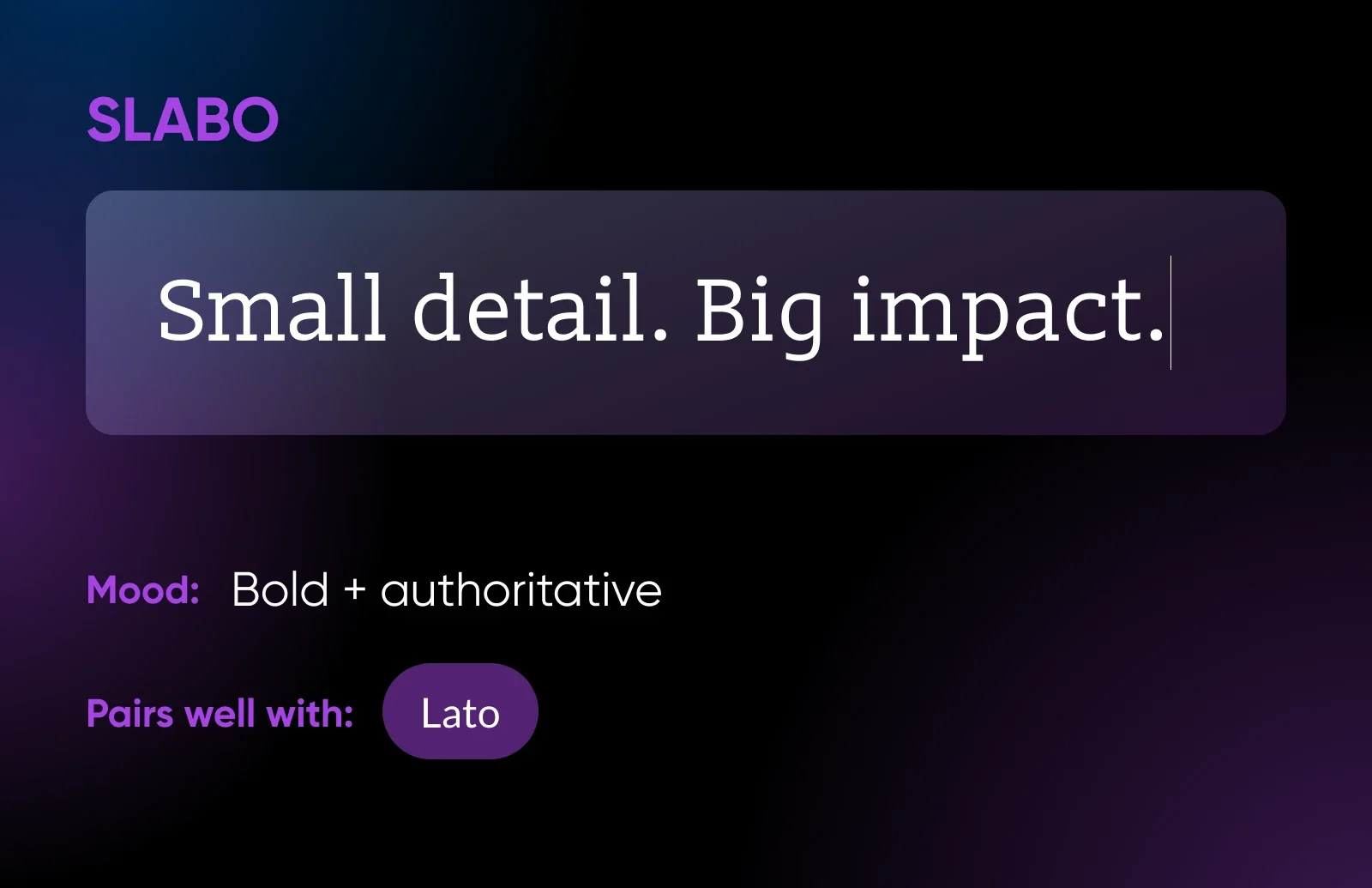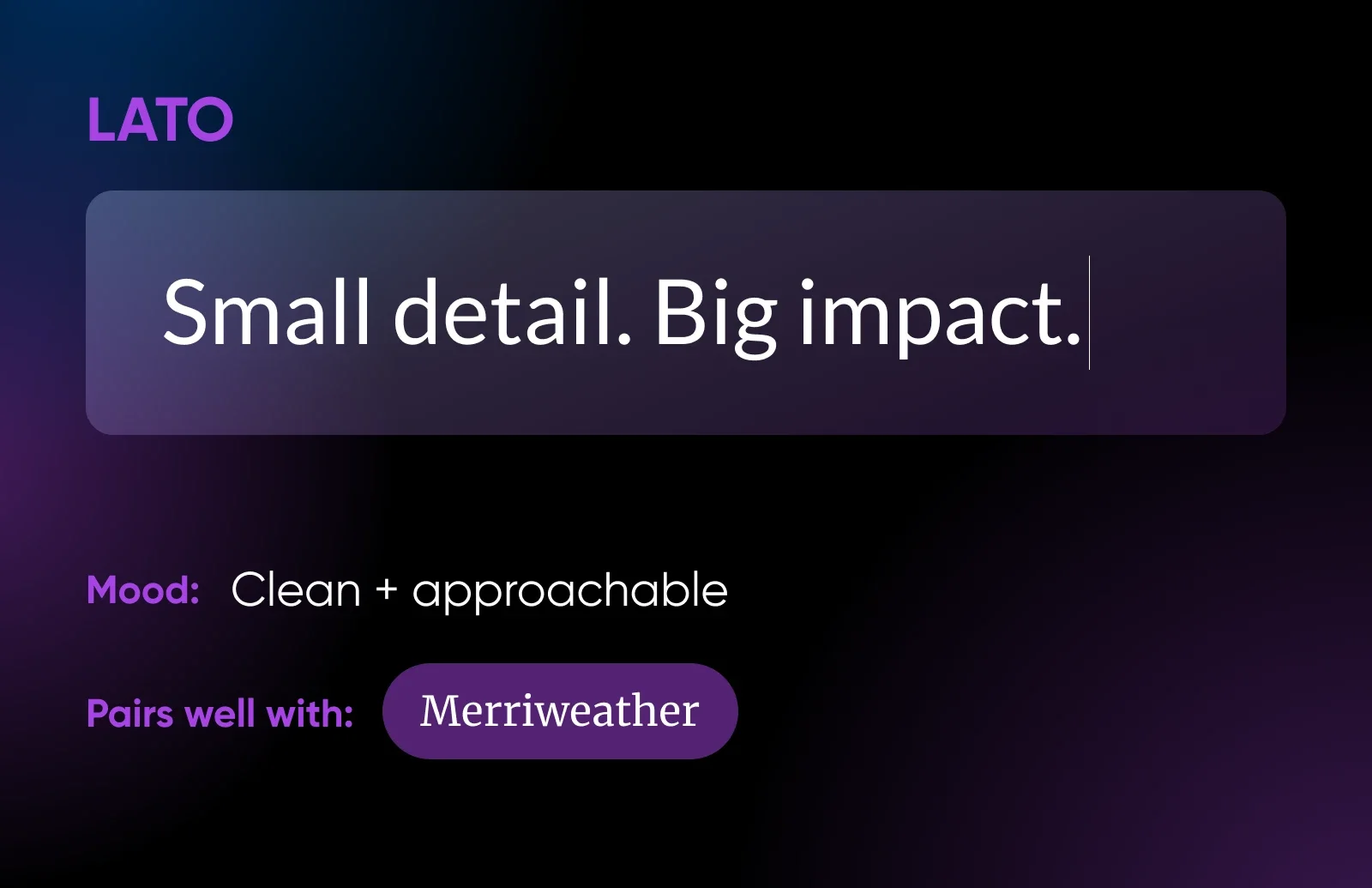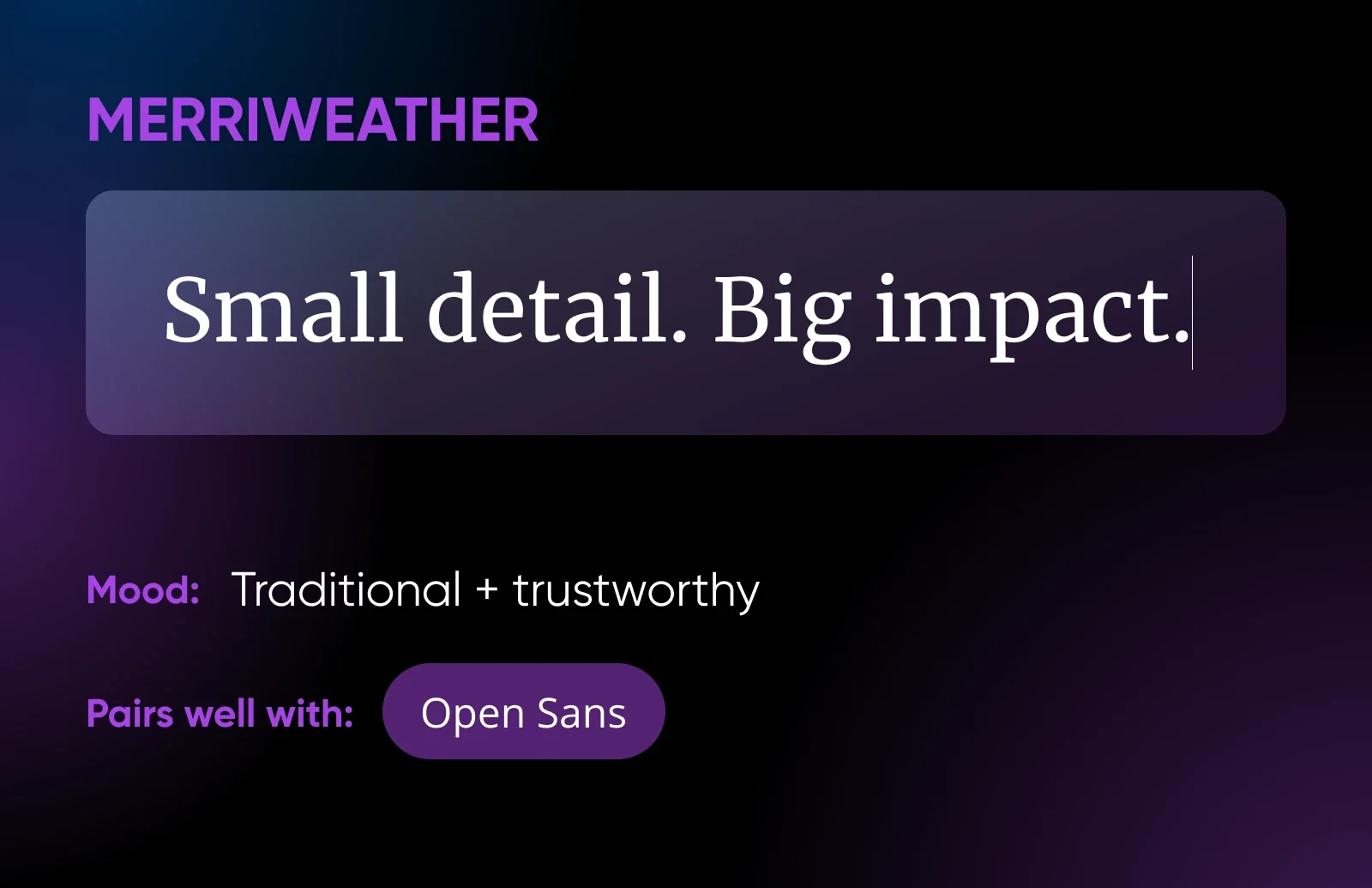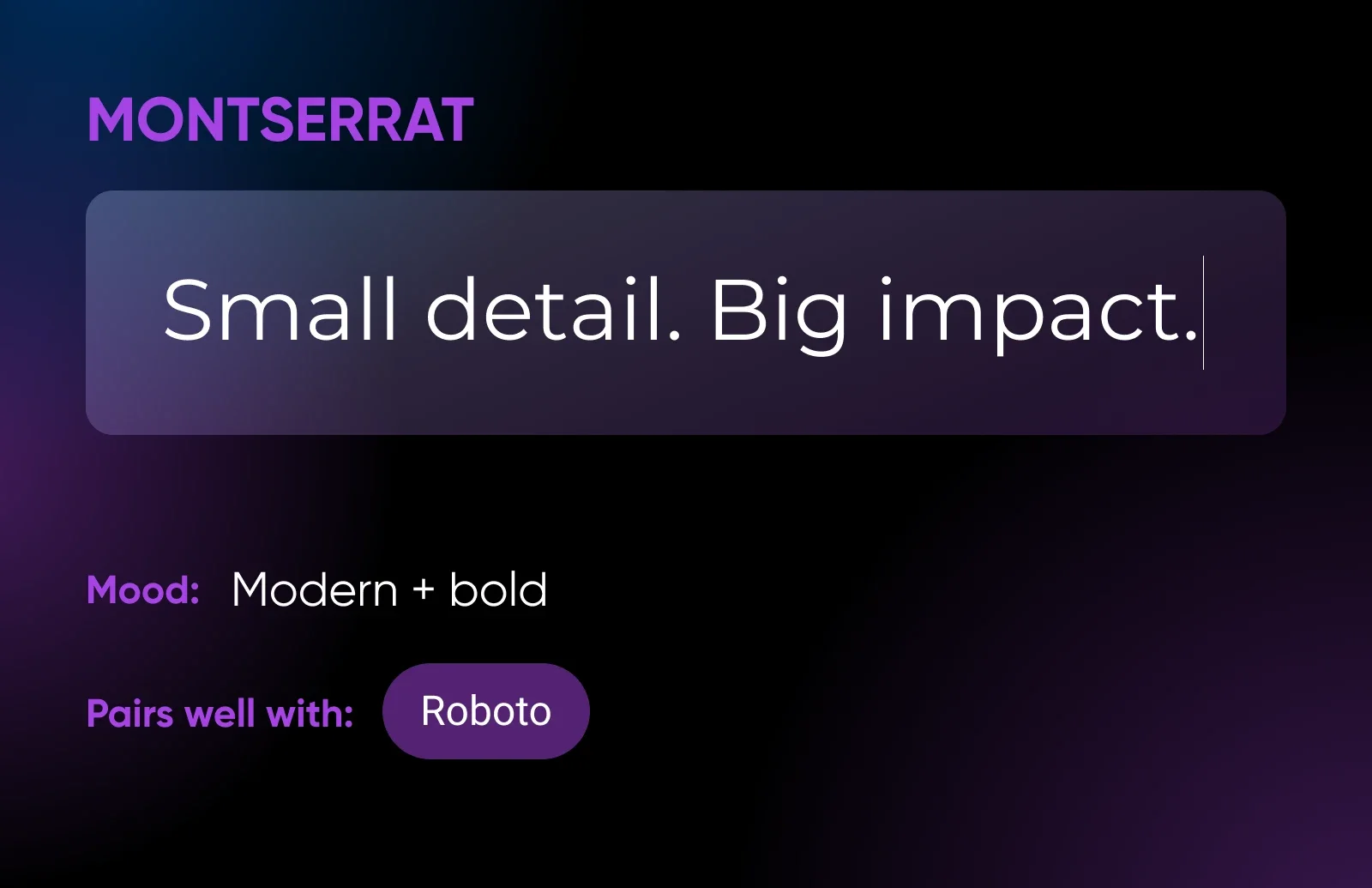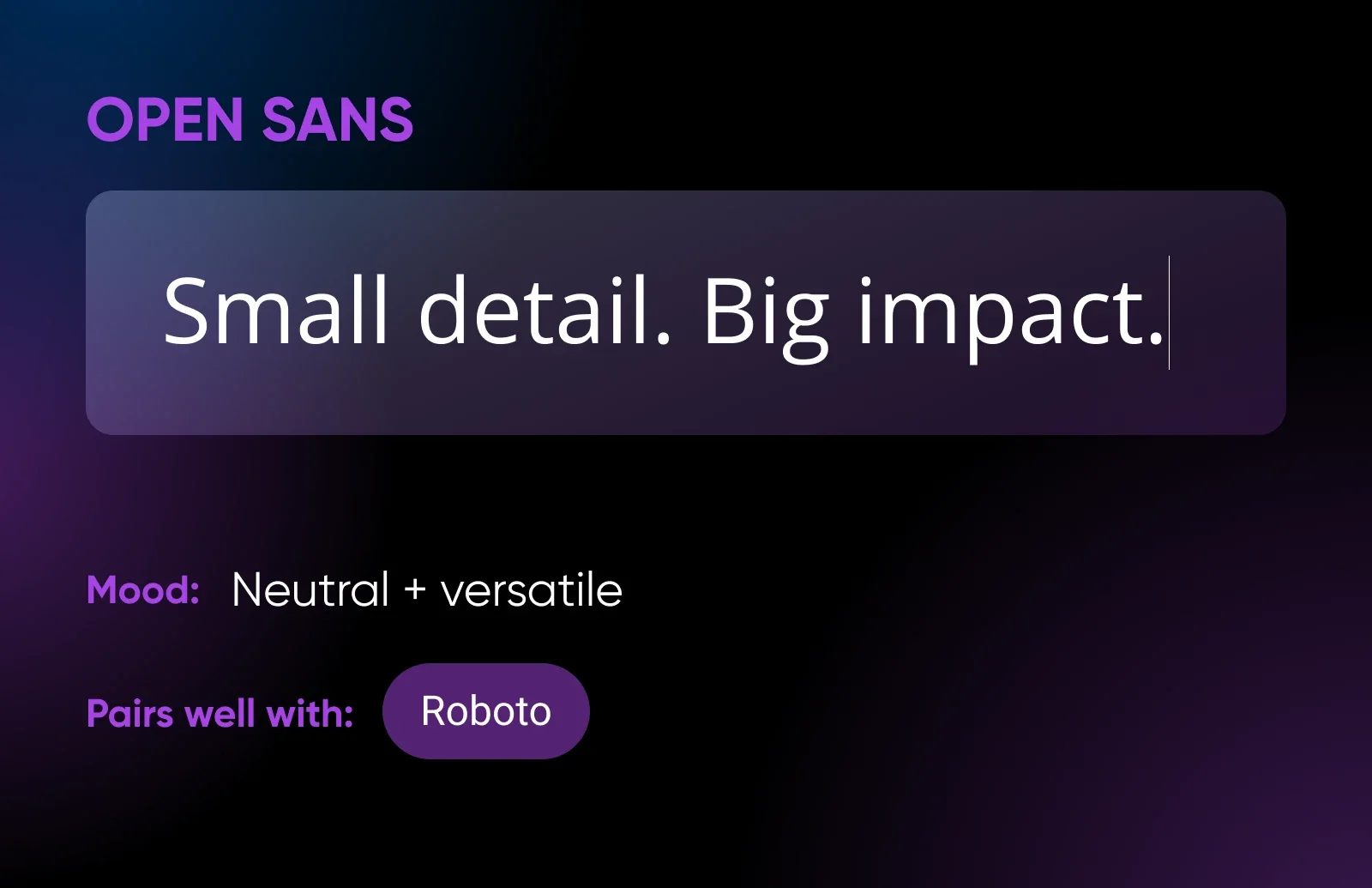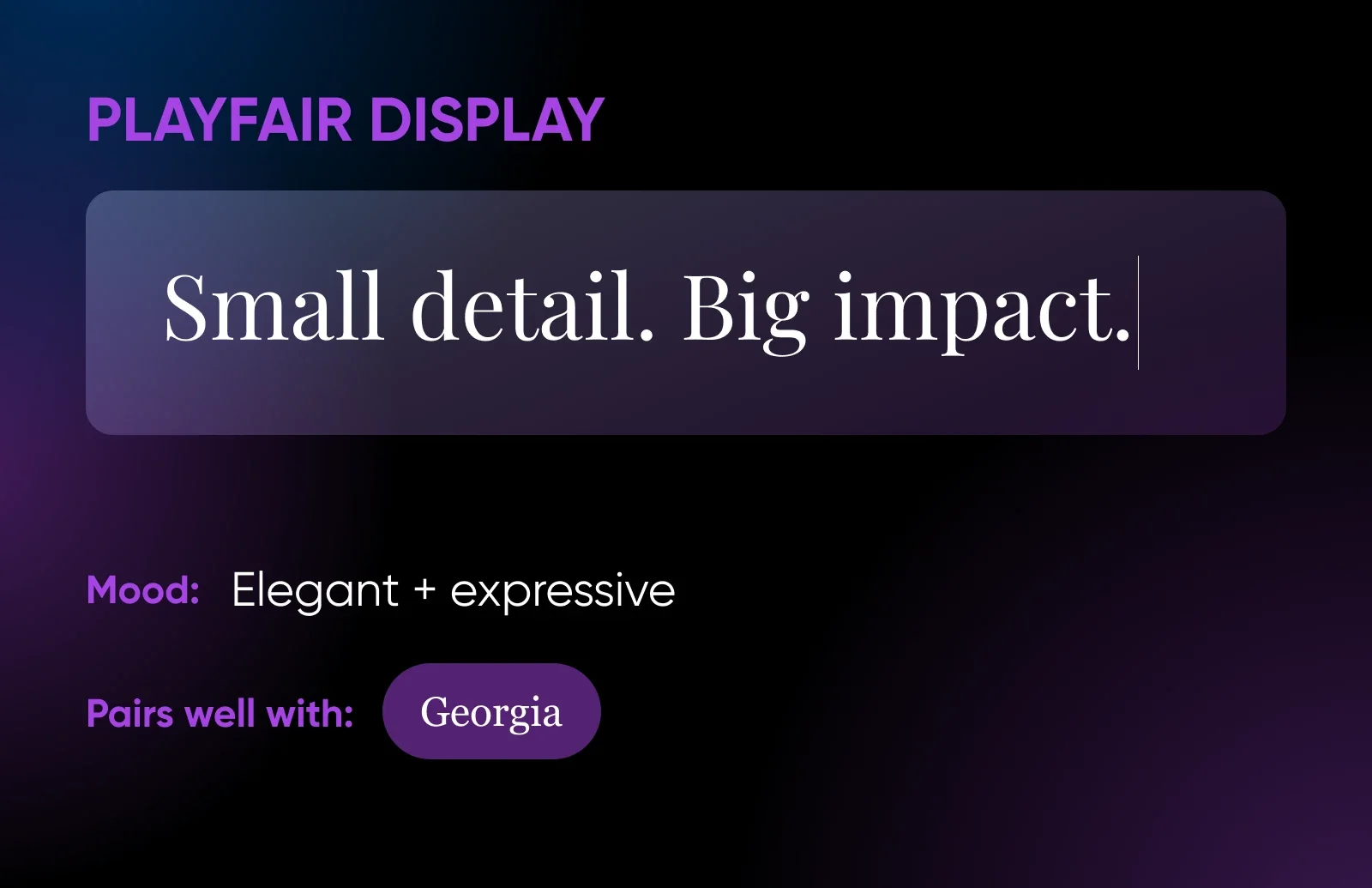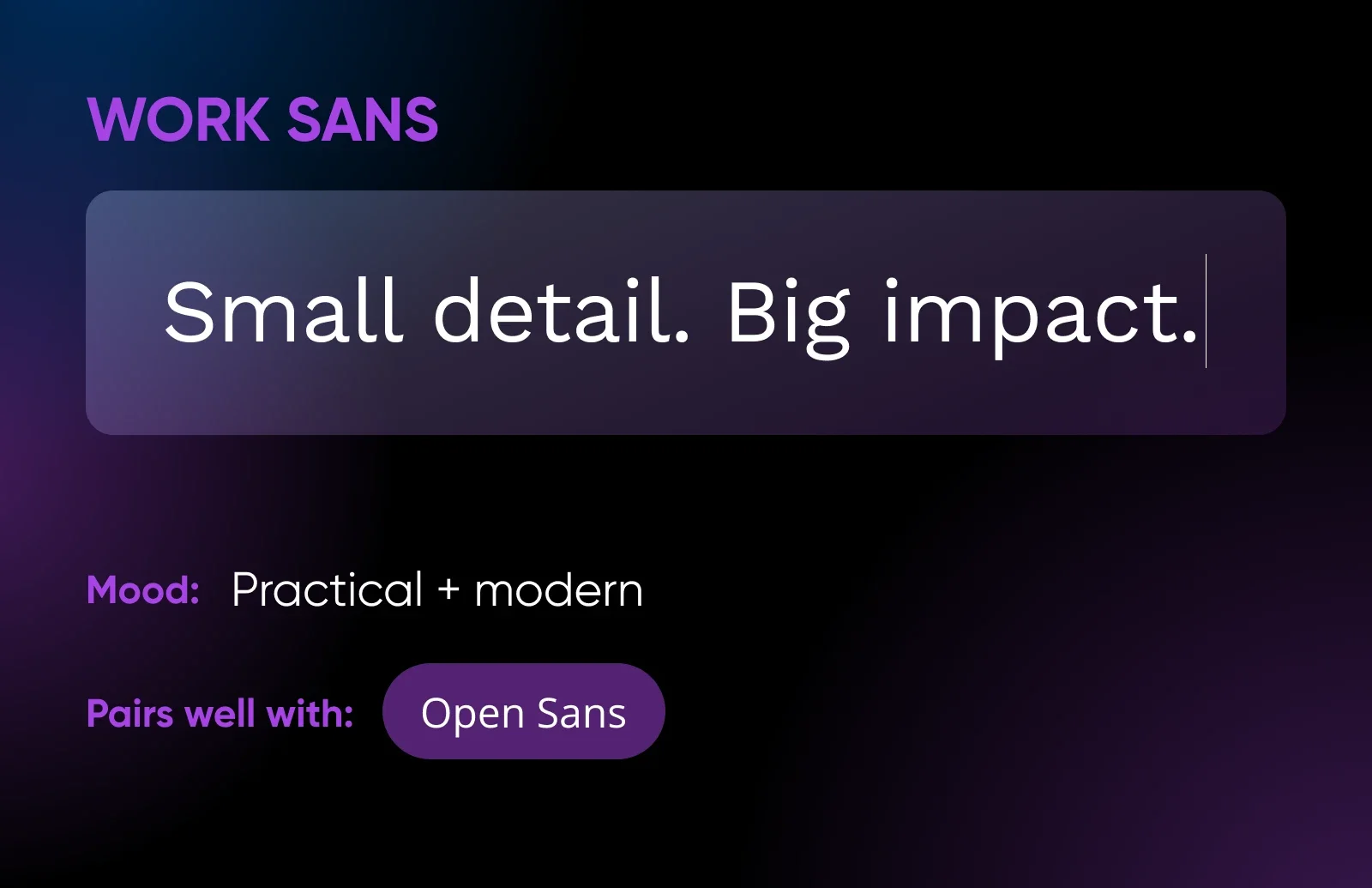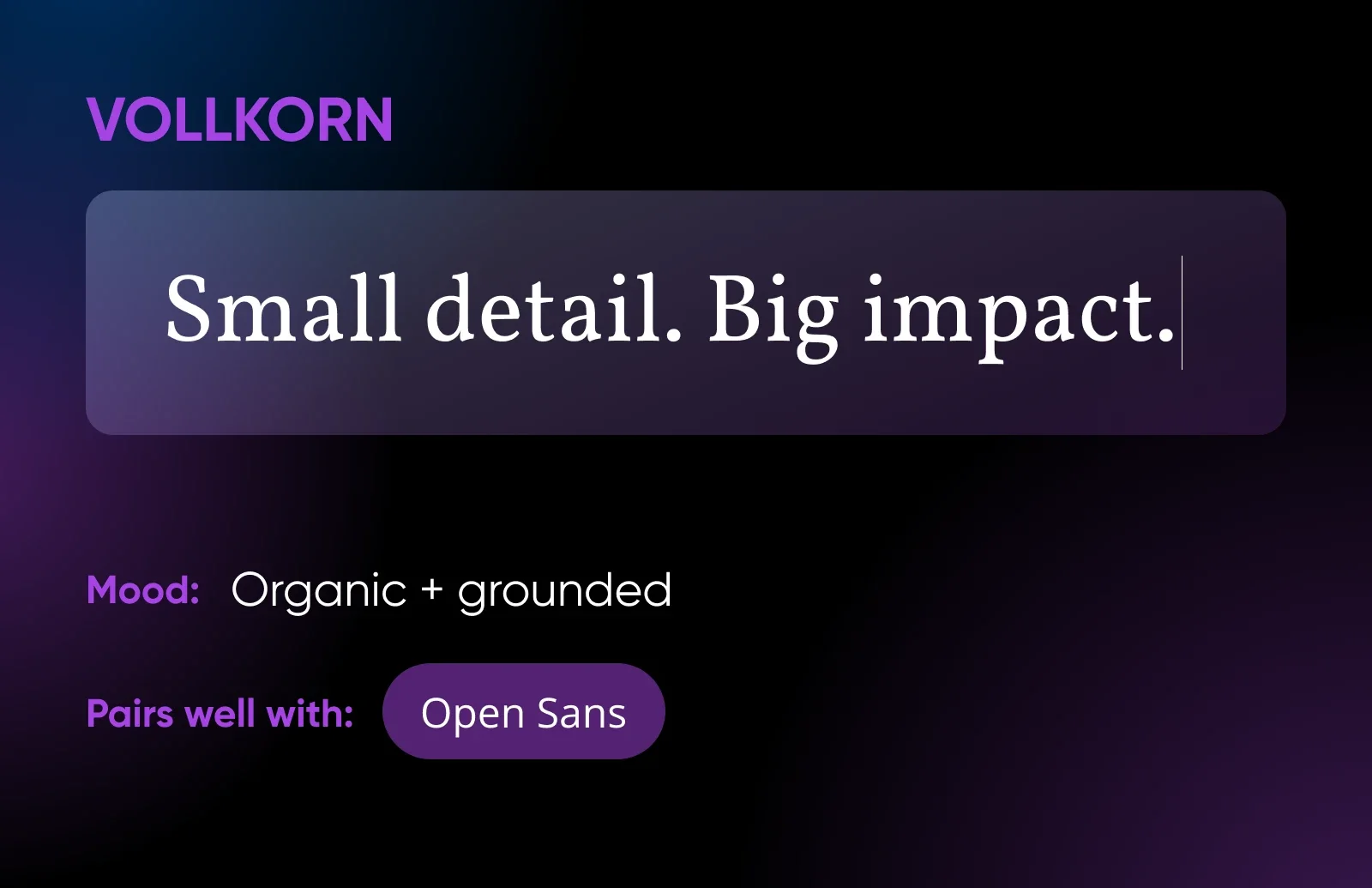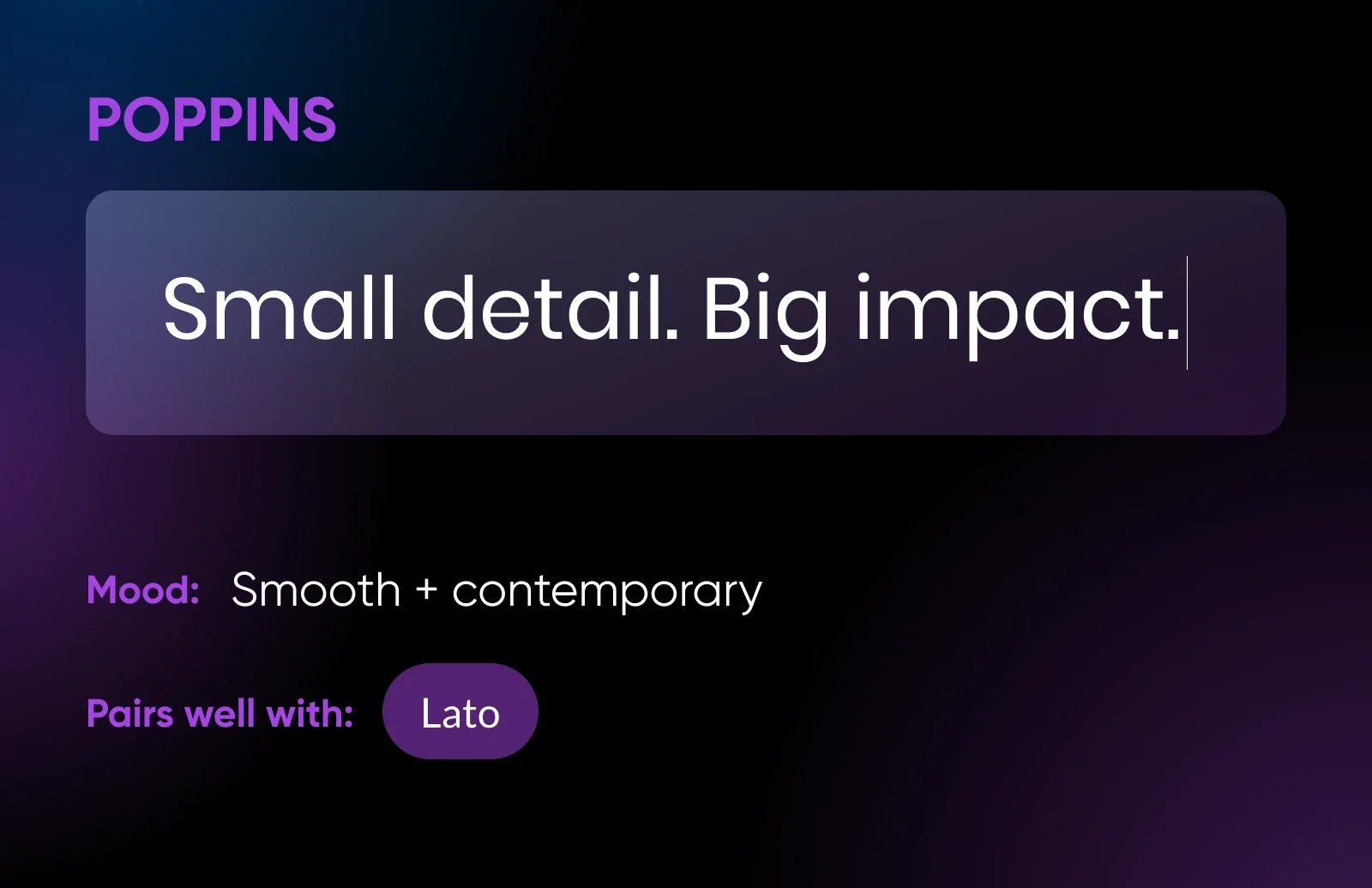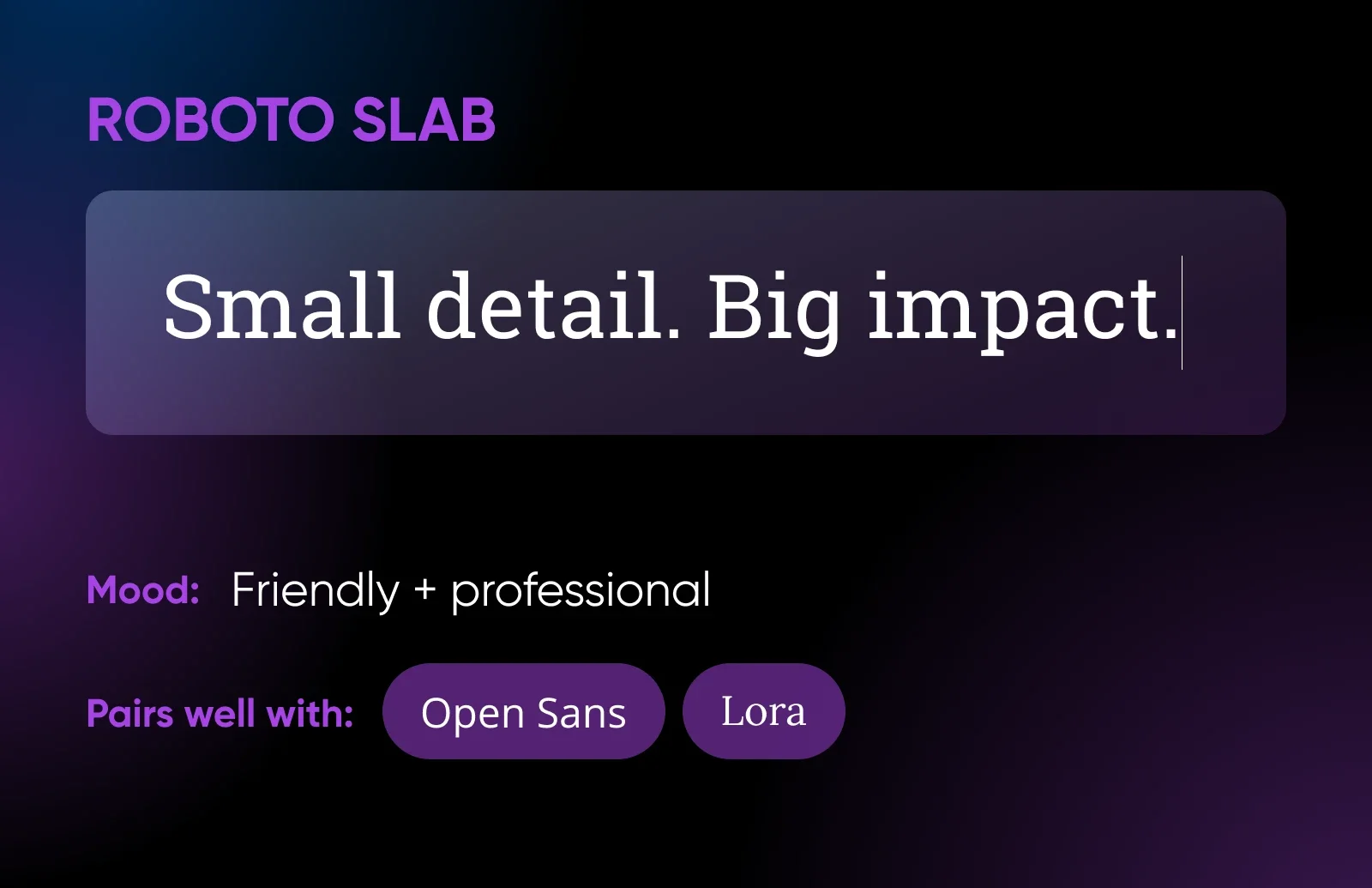
Каждый может оценить удачный выбор шрифта. Он делает чтение приятным и усиливает общий дизайн сайта.
Однако подобрать подходящий шрифт для своего сайта почему-то кажется очень сложным. В Google Fonts представлено почти 2000 бесплатных семейств шрифтов с открытым кодом (1942 по состоянию на июль 2026 года, согласно каталогу). Как вообще сузить выбор?
Вероятно, поэтому вы здесь. И мы рады помочь.
Краткий ответ: Лучшие шрифты Google для большинства сайтов — это проверенные, читаемые семейства, такие как Roboto, Open Sans, Lato, Montserrat и Merriweather. Лучший шрифт для вашего сайта зависит от индивидуальности бренда — поэтому ниже мы сгруппировали 20 отличных вариантов по стилю, с рекомендациями по сочетанию для каждого.
Будь вы в поиске утончённого и изысканного или весёлого и яркого, здесь найдётся подходящий вариант.
Готовы погрузиться? Давайте начнём.
Как выбрать подходящие шрифты для вашего сайта
Большинство владельцев сайтов на самом деле не выбирают шрифт. Они просто используют тот, который стоит по умолчанию в выбранной теме.
Это нормально (в большинстве случаев). Но стоит потратить несколько минут на осознанный выбор.
Почему? Потому что выбор шрифта может повлиять на:
- Как люди воспринимают ваш бренд
- Уровень доверия потенциальных клиентов
- Насколько легко ориентироваться на вашем сайте
- Будут ли люди читать ваш контент
- Насколько легко люди смогут совершать покупки
Хм, получается, выбор шрифта может как создать, так и разрушить весь ваш бренд. Круууто…
Не волнуйтесь, однако. Выбор хорошего шрифта — не ракетостроение. Просто следуйте этим золотым правилам:
- Выберите правильную «индивидуальность»: Каждый шрифт имеет свой характер. Одни кажутся формальными и корпоративными. Другие — драматичными, футуристичными или детскими. В идеале ваш шрифт должен соответствовать настроению вашего бренда и нравиться целевой аудитории. (Мы опишем некоторые из лучших вариантов позже.)
- Ставьте на читаемость: В Google Fonts есть всё — от простых букв до каллиграфического рукописного текста. Хотя экспериментировать со стильными шрифтами можно, всегда ставьте комфорт чтения выше эстетики, потому что усталость глаз существует.
- Выбирайте не больше двух: Вам не нужно больше. А добавление дополнительных шрифтов только ухудшит производительность вашего сайта.
Другими словами, всё сводится к созданию правильной визуальной атмосферы и сохранению простоты.
Шрифты с засечками и без засечек
Вы наверняка слышали термины «шрифты с засечками» (serif) и «шрифты без засечек» (sans serif).
Засечка — это маленькая «ножка», которую иногда можно увидеть внизу букв. Она как бы имитирует росчерк, который вы делаете, отрывая перо от бумаги.
Шрифты с засечками имеют такие ножки. Шрифты без засечек — нет.
И это важно, потому что…
Ну, эти ножки действительно сильно влияют на общий вид шрифта.
- Шрифты с засечками обычно кажутся классическими, традиционными и надёжными. Отчасти потому, что их часто используют в книгах и газетах. Они могут быть очень читаемыми, хотя лучше всего работают на дисплеях с высоким разрешением.
- Шрифты без засечек выглядят более современными, чистыми и прямолинейными. Без ножек, о которые можно споткнуться, эти шрифты суперчитаемы на любых экранах. Но простота может также означать некоторую скучность.
Коротко: Выбирайте шрифты с засечками, если хотите более традиционный, интеллектуальный вид. Выбирайте шрифты без засечек для гладкого, современного облика. Сочетайте их для получения лучшего из обоих миров.
20 шрифтов Google для любого сайта малого бизнеса
Хватит теории веб-дизайна. Давайте перейдём к реальным шрифтам.
Вместо того чтобы вываливать на вас огромный список, мы разделили наши рекомендации по настроению. Ищите заголовок, который лучше всего соответствует вашему сайту, чтобы найти идеальные шрифты!
💼 Мощные шрифты для профессионалов
Будь вы юридический орел, медицинский работник или финансовый гений, шрифт вашего сайта должен произвести впечатление на посетителей.
Вот несколько элегантных, изысканных вариантов для пробы.
1. Roboto Slab
Roboto Slab — это гарнитура с открытыми изгибами, которая позволяет буквам занимать столько места, сколько им нужно. Это значит, что посетители будут наслаждаться плавным чтением при любом размере шрифта.
Этот шрифт хорошо сочетается с длинным списком шрифтов без засечек, таких как Lato и Open Sans.
2. Merriweather
Merriweather был разработан для лёгкого чтения на экранах. Он отличается лёгким диагональным наклоном — это значит, что самые тонкие части букв наклонены для динамичного ощущения.
Тем не менее, общий вид довольно традиционный, поэтому ваш бренд будет восприниматься как «проверенный временем» вариант.
Этот шрифт отлично сочетается с Merriweather Sans.
3. Noto Serif
Гибрид классики и современности, Noto Serif предлагает отличную читаемость и утончённый стиль, идеально подходящий для профессиональных сайтов. Благодаря слегка сжатым формам букв этот шрифт хорошо работает в ограниченном пространстве.
Он хорошо сочетается с чистыми шрифтами без засечек, такими как Lato и Open Sans.
4. Libre Baskerville
Libre Baskerville — это адаптированная для цифровых экранов версия классического шрифта Baskerville, известного своей элегантностью и читаемостью в печати.
Традиционный стиль был доработан для лучшей чёткости на экране, но сохранил много изысканности. Сочетайте его с Lora для эффекта «засечка на засечку» или с Montserrat для современного контраста.
5. Slabo
Созданный специально для веба, Slabo выпускается в версиях, привязанных к конкретному размеру: каждая из них оптимизирована для точного размера в пикселях, указанного в названии (13px для текста основного размера, 27px для более крупных заголовков). При использовании в предназначенном размере он отображается чётко на любом экране.
Общий вид — гладкий и профессиональный, что делает его хорошим выбором для деловых сайтов. Он хорошо сочетается с Lato.
🎨 Захватывающие шрифты для творческих людей
Если вы хотите, чтобы вас знали как творческую личность, последнее, что вам нужно, — это скучная гарнитура.
Вот несколько привлекательных, заметных вариантов, которые понравятся вашим посетителям:
6. Playfair Display
Под влиянием дизайна XVIII века этот шрифт идеально подходит для сайтов с ноткой классической элегантности.
Playfair Display передает сильное ощущение авторитетности, а жирный стиль может выделить заголовки на занятой странице. Он хорошо сочетается с веб-безопасной классикой Georgia или ее вариантом в верхнем регистре, Playfair Display SC.
7. Lato
Чистые линии Lato изначально были созданы как набор корпоративных шрифтов. Но в этой гарнитуре есть много теплоты и даже доля причудливости.
Он отлично подходит для портфолио и сайтов агентств, как для заголовков, так и для основного текста. Сочетайте его с Merriweather, когда хотите получить контраст с засечками.
8. Montserrat
Созданный известным графическим дизайнером Хулиетой Улановски, Montserrat был вдохновлен старыми плакатами и вывесками Буэнос-Айреса. Он отражает красоту городской типографики.
Современная версия была сделана более легкой, что делает его более подходящим для длинных текстов. Он хорошо сочетается с Roboto.
9. Poppins
Современный геометрический гротеск, Poppins красиво гладкий и округлый. Он хорошо работает на сайтах, где вы хотите добавить нотку современного стиля, не жертвуя читабельностью.
Он фаворит в техническом сообществе, но также заставит ваше портфолио выделяться в сочетании с Lato.
10. Raleway
Технически вы можете использовать Raleway как шрифт без засечек для основного текста. Но, по правде говоря, эта элегантная гарнитура лучше всего смотрится в крупном размере.
В нем все линии чистые, а углы острые, что добавляет современную четкость портфолио, сайтам агентств, личным блогам и многим другим проектам. Open Sans станет естественным партнером для основного текста.
💻Современные шрифты для цифрового поколения
Создаете программный бизнес или ведете блог о последних технологиях? В любом случае вам нужен шрифт, который выглядит передовым.
Эти чистые современные варианты должны подойти:
11. Open Sans
Как гуманистический гротеск, Open Sans был разработан, чтобы выглядеть чистым и нейтральным. Это делает его отличным выбором для основного текста в самых разных веб- и мобильных проектах.
Он хорошо работает в сочетании с Roboto или как контраст к Merriweather.
12. Roboto
Roboto доступен в 18 начертаниях. Это также вариативный шрифт, поэтому вы можете точно настроить его насыщенность и ширину по своему вкусу. Формы букв немного геометричны, что прекрасно уравновешивается мягкими открытыми кривыми.
Такое сочетание делает Roboto дружелюбным, но в то же время достаточно профессиональным для бизнес-сайтов. Используйте его для заголовков или основного текста; сочетайте с Lora.
13. Fira Sans
Fira Sans изначально был заказан Mozilla, организацией, стоящей за браузером Firefox, для своей мобильной платформы Firefox OS. Это наследие проявляется в чистых открытых формах букв.
Обеспечивая отличную четкость на всех экранах, Fira Sans хорошо подходит для мобильных версий сайтов, мобильных приложений и платформ для чтения. Попробуйте объединить его с Lato.
14. Work Sans
Как следует из названия, эта гарнитура была создана для профессионального использования. В контексте веб-дизайн проектов она является хорошим выбором везде, где важна разборчивость — особенно на небольших экранах.
Сочетайте с Open Sans для суперчистого вида.
15. Source Code Pro
Source Code Pro — это моноширинный шрифт, то есть каждый символ занимает одинаковую ширину. Это делает его отличным для сред программирования и других ситуаций, где разборчивость имеет решающее значение.
Он также может работать как изысканный шрифт для основного текста с оттенком "гиковости". Сочетайте его с Roboto, чтобы остальная часть страницы оставалась доступной.
🤝Дружелюбные шрифты для лайфстайл-брендов
От кафе до коучинга, многие бизнесы основаны на личных связях. Шрифты, которые кажутся расслабленными и дружелюбными, обычно являются лучшим выбором для этих лайфстайл- и локальных брендов.
Вот несколько хороших примеров:
16. Vollkorn
В немецком языке Vollkorn означает "цельное зерно". Шрифт оправдывает это описание, имея органичный, натуральный вид. Он приглашает посетителей читать ваш контент у камина с чашкой какао.
Как таковой, Vollkorn лучше всего подходит для сайтов, связанных с ремеслами, едой или природой. Сочетайте его с нейтральными гротесками, такими как Open Sans.
17. Lora
Lora — это современный, хорошо сбалансированный шрифт с корнями в каллиграфии. У него красивые кистевые изгибы и округлые засечки, но ничего слишком вычурного.
Общий вид очень чистый. И это делает Lora отличным выбором как для основного текста, так и для заголовков. Сочетайте его с Lato, чтобы завершить образ.
18. PT Serif
Забавный факт: PT Serif был разработан для "Общедоступных шрифтов Российской Федерации".
Буквы этого шрифта длинные и элегантные, а сочетание тонких и толстых штрихов делает его легким для чтения на многих разных языках. Он отлично сочетается с PT Sans.
19. Indie Flower
Беззаботный и открытый, Indie Flower имеет игривый характер. Он немного смелее некоторых рукописных шрифтов, и между буквами больше места, что обеспечивает дополнительную ясность для ваших читателей.
Используйте его вместе с Noto Sans для хорошего баланса между стилем и функциональностью.
20. Caveat
Caveat был разработан для коротких аннотаций и основного текста. Его функции OpenType позволяют буквам иметь небольшие вариации в зависимости от их положения в слове.
Например, буква может выглядеть более "рукописной" в некоторых случаях. Слегка неровная природа этого шрифта добавляет органичности лайфстайл-сайтам. Вы можете сбалансировать это чистыми формами Open Sans.
Как выбрать идеальную пару шрифтов
Надеюсь, хотя бы один из этих шрифтов пришелся вам по душе.
Вы можете просто взять его и остановиться на этом. Дело сделано.
Однако, как правило, мы рекомендуем использовать два шрифта. Это создает визуальный контраст, который выглядит хорошо и помогает посетителям ориентироваться в вашем контенте.
Например, у вас может быть один шрифт для заголовков, титулов и подписей, а другой — для основного текста.
Конечно, два шрифта всё равно должны работать вместе. Вот как подобрать идеальную пару.
- Используйте жирный, выразительный шрифт для заголовков: Смысл в том, чтобы привлечь внимание! Если текст читабелен, здесь можно проявить креативность.
- Выбирайте чистый, читаемый шрифт для основного текста: Если вы хотите, чтобы посетители продирались сквозь ваши записи в блоге и описания товаров, нужно выбрать шрифт, который легко читать.
- Создавайте визуальный контраст, не вызывая хаос: Мы ищем шрифты, которые дополняют друг друга, а не конфликтуют. Им нужно иметь что-то общее.
- Попробуйте классическую комбинацию с засечками и без засечек: Используйте один для заголовков, другой для основного текста. Неважно, какой из них будет для чего.
- Либо комбинируйте разные версии одного семейства шрифтов: Например, Roboto отлично сочетается с Roboto Condensed или Roboto Mono.
Подбор шрифтов, очевидно, дело вкуса. Но есть несколько проверенных комбинаций, которые работают всегда.
Вот ваша шпаргалка:
| Тип бизнеса | Заголовочный шрифт | Основной шрифт | Почему это работает |
|---|---|---|---|
| Юридические/профессиональные услуги | Merriweather | Open Sans | Вызывает доверие и читабельность |
| Креативное агентство | Playfair Display | Lato | Элегантно, но доступно |
| Технологический стартап | Montserrat | Roboto | Современно и чисто |
| Местное кафе/лайфстайл | Vollkorn | PT Sans | Тепло и приветливо |
| Электронная коммерция | Oswald | Source Sans 3 | Выразительно и удобно для пользователя |
Лучшие практики использования Google Fonts
Настроить выбранные Google Fonts довольно легко. Если вы используете WordPress с блочной темой (если вы видите «Внешний вид → Редактор» в панели управления, значит, у вас блочная тема), вам даже не нужен плагин: встроенная библиотека шрифтов (добавлена в WordPress 6.5) позволяет устанавливать Google Fonts прямо из панели стилей редактора сайта. В классической теме плагин всё ещё может сделать эту работу за вас.
Но прежде чем двигаться дальше, мы рекомендуем выполнить несколько предварительных проверок. Лучше исправить проблемы заранее, чем потом обнаружить, что ваш сайт нечитаем!
Вот контрольный список:
- Выбирайте начертание 400 или 600 для основного текста: Более лёгкие начертания обычно лучше подходят для заголовков. Они теряются при маленьком размере шрифта.
- Загружайте только те начертания и стили шрифтов, которые вам нужны: Сюда входят Regular, Bold, Italic и так далее. Чем больше вы добавляете, тем больше влияние на скорость загрузки страницы.
- Тестируйте новые шрифты на разных устройствах: Некоторые шрифты сложнее читать на маленьких экранах. Возможно, вам придётся увеличить размер шрифта для мобильных устройств или переключиться на другой шрифт.
- Оптимизируйте загрузку шрифтов: Оставьте настройку
font-display: swap(строка CSS, которая уже включена в стандартный код встраивания Google Fonts), чтобы текст оставался видимым во время загрузки шрифта. О предзагрузке и других трюках для ускорения читайте наше руководство по предотвращению проблем с производительностью веб-шрифтов. - Рассмотрите вариативный шрифт: Многие популярные семейства, включая Roboto, Open Sans и Montserrat, теперь являются вариативными шрифтами. Один файл покрывает целый диапазон начертаний, давая вам гибкость дизайна без лишних загрузок.
- Размещайте шрифты на своём хостинге, если у вас есть посетители из ЕС: Загрузка шрифтов с серверов Google передаёт IP-адреса посетителей Google, и немецкий суд в 2022 году постановил, что это без согласия нарушает GDPR. Скачивание шрифтов и их обслуживание с вашего собственного хостинга обходит эту проблему. (Установленные шрифты через библиотеку шрифтов WordPress уже обслуживаются с вашего сайта.)
- Не забывайте про языки: Думаете о публикации на нескольких языках? Убедитесь, что ваш шрифт поддерживает все нужные символы.
Часто задаваемые вопросы о Google Fonts
Сколько шрифтов в Google Fonts?
По состоянию на июль 2026 года в каталоге Google Fonts насчитывается 1 942 семейства шрифтов, и библиотека продолжает расти. Большинство семейств включают несколько начертаний и стилей, и все они бесплатны и с открытым исходным кодом.
Бесплатны ли Google Fonts для коммерческого использования?
Да. Каждый шрифт в библиотеке выпускается под открытой лицензией (в основном используется SIL Open Font License), поэтому вы можете использовать их в личных и коммерческих проектах бесплатно, включая работу с клиентами, логотипы и печатную продукцию.
Какие шрифты Google самые популярные?
Согласно рейтингу популярности Google Fonts (июль 2026 года), наиболее используемые семейства включают Roboto, Open Sans, Google Sans, Inter, Montserrat и Poppins. Популярность не означает автоматически, что шрифт подходит для вашего бренда, но эти шрифты заслужили свою репутацию читабельностью.
Какой шрифт использует Google в своём логотипе?
Логотип Google использует Product Sans, собственный шрифт, который нельзя скачать. Хорошая новость: в конце 2025 года Google выпустил на Google Fonts близкий родственный шрифт Google Sans (плюс Google Sans Flex), так что теперь вы можете получить такой же вид бесплатно. Poppins и Montserrat — аналогичные геометрические варианты.
Замедляют ли Google Fonts ваш сайт?
Любой веб-шрифт добавляет немного времени загрузки, но влияние остаётся небольшим, если загружать только нужные начертания и оставить включённой CSS-настройку font-display: swap. Размещение файлов шрифтов на своём хостинге также может убрать дополнительное сетевое соединение.
Какие шрифты Google хорошо сочетаются друг с другом?
Надёжные комбинации включают Playfair Display с Lato, Merriweather с Open Sans и Montserrat с Roboto. Общее правило: выберите один выразительный шрифт для заголовков и один легко читаемый шрифт для основного текста.
Оптимизируйте свой сайт с помощью шрифтов
Создаёте ли вы оживлённый новостной сайт или минималистичный шедевр, Google Fonts должны покрыть ваши типографические потребности. Огромное количество бесплатных шрифтов — это безумие.
На самом деле ваша главная задача — сузить выбор. Просто держите эти принципы в голове:
- Не более двух шрифтов.
- Убедитесь, что они соответствуют вашему бренду и подходят вашей аудитории.
- Сосредоточьтесь на читабельности.
- Ищите подходящую пару или используйте старую комбинацию с засечками и без.